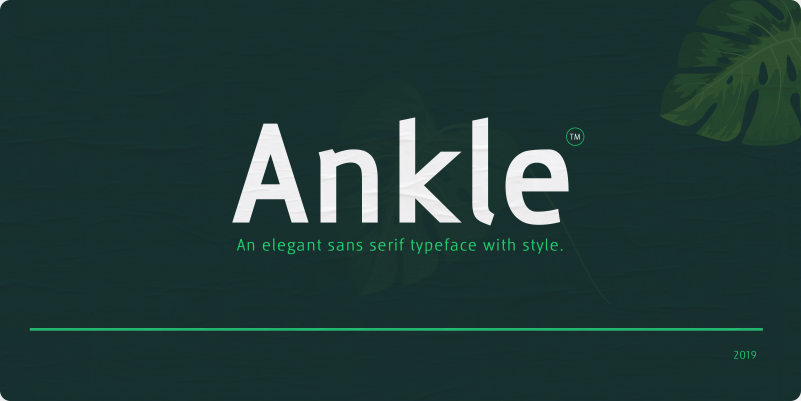
Ankle Sans Font – Download Grátis
Ankle Sans é uma elegante tipografia sans serif com estilo moderno e sofisticado. Criada por Vikers | RerdSystems, esta fonte deixa um visual minimalista mas profissional que combina bem tanto para logotipos quanto para posters e materiais gráficos. Seu design arredondado e geometrized dá-lhe uma aparência futurista sem perder a elegância clássica. Suas linhas sutilmente curvadas proporcionam um toque sofisticado, fazendo Ankle Sans um ótimo recurso para projetos que necessitam de um aspecto clean e contemporâneo. Além disso, é perfeitamente adaptável às diversas necessidades do design gráfico, desde a criação de materiais publicitários até a personalização de logotipos. Ankle Sans atende a uma variedade de estilos, incluindo o moderno, o clássico e até mesmo o ultra-minimalista, tornando-a versátil em qualquer aplicação visual. Com sua simplicidade perfeita e sofisticação contida, Ankle Sans é um recurso gráfico indispensável para designers atentos à estética moderna.